敏捷的棕色狐狸跳过了那只懒狗。对于那些关注字体和版式艺术的人来说,这就是著名的pangram。如果您从未听说过,那么该是离开竞技场的时候了,因为当我们进入下面提到的某些字体游戏时,战斗可能会血腥起来。会有很多紧缩,只有坚强的角色才能生存。您不能转弯。
好吧,我确实设法在其中嬉戏地输入了一些字体。但这一切都指出,玩排版很有趣。如果您发现有关字体和字体的Web应用程序很有趣,那么您几乎不需要哄哄。 《 Kern Type》是一款以娱乐性和视觉愉悦的方式教授这一原理的游戏。屏幕上显示由不同字体组成的单词。您对字体间距的准确度得分很高。您的工作将与设计师(打字员)的工作进行比较,如果做对了,您的得分将会很高。该游戏可以真正丰富您的知识,因为您不仅在学习排版的美学知识,而且还学习字体,字体的起源以及其背后的设计师。
形状类型
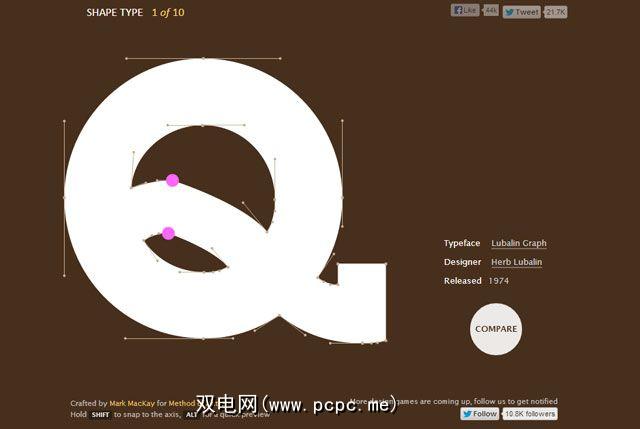
Shape Type是一款比上述游戏更难的游戏。您必须将字母的轮廓拖到屏幕上,然后创建形状适当,美观的字母。字母被故意弯曲变形,而您对字体的熟悉程度将决定您如何正确地正确调整它们的形状。您会再次接近原始图像。
核类型和形状类型由马克·麦凯(Mark Mackay)开发。两种HTML5游戏都具有多点触摸功能,并且可以在触摸屏上播放。
TypeConnection
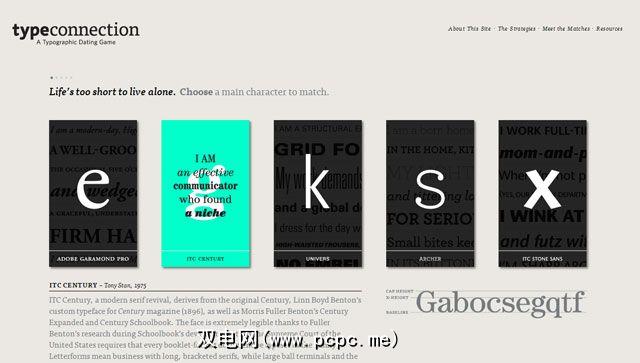
我们之前已经详细介绍了设计极为出色的“排印约会游戏"。字体还需要一种叫做和声的东西才能和谐共处。就像现实生活中的角色一样,寻找与伴侣之间良好关系的最佳选择。 TypeConnection允许您播放丘比特并使字体相互匹配。只有最好的夫妻才能做到。您可能正在扮演天使,但也有很多收获—学习印刷术术语,类型历史,以及正确的配对。如果您真的想真正输入文字并了解印刷术的更多信息,那么该网站的“资源"页面是一个宝库。
我喜欢印刷术
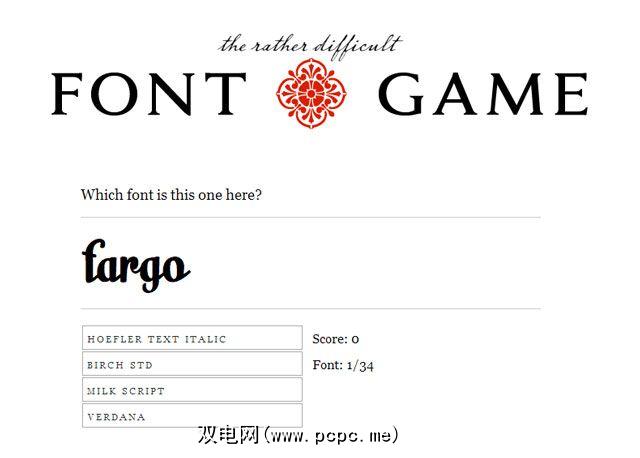
这是一个简单的字体标识游戏。系统会以四种可能的答案的形式为您提供字体和提示。正确对待它们,您的分数就会提高。您可能喜欢排版,但是如果您来自仅由Ariel,Times Roman和Comic Sans统治的地方,那么这是一个困难的游戏。您还可以使用移动版本并随身携带,以使移动时的字体知识更加轻松。
Ragtime
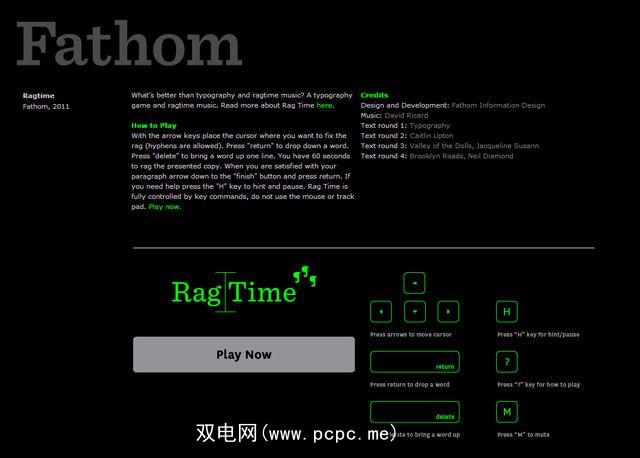
“标记不完整"是指沿页边距的印刷对齐方式。更具体地说,该行在段落的右侧断开。字体对齐对于所需的设计输出极为重要。 Ragtime是一款定时游戏(60秒),它会挑战您使用方向键来修复文本块。您必须始终使用箭头键正确对齐文本,同时还要在ragtime音乐在背景中嗡嗡作响时一直集中注意力。
拍摄衬线
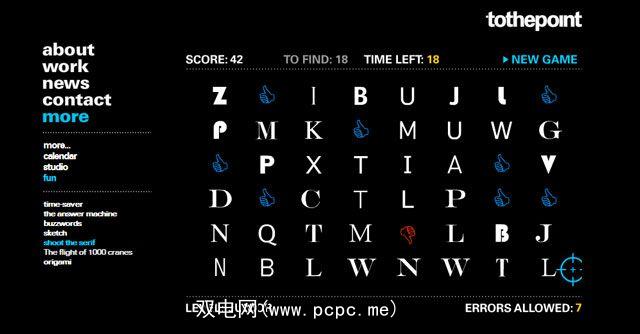
一个建议。请勿将耳机插入最大音量。枪声几乎把我的耳朵打断了。但这就是游戏,您可以在其中证明找到衬线并将其击落的速度。您必须在争分夺秒地射击。该游戏具有多个级别,而且难度逐渐增加……但是最终,您可以掌握枪支,并清楚了解衬线字体和无衬线字体之间的区别。
Helvetica
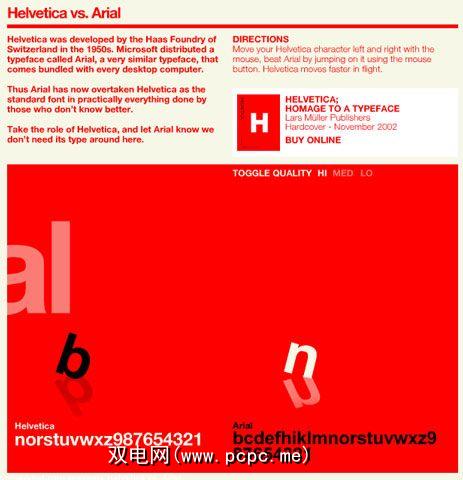
这是一个报仇和报应的故事。上面的屏幕截图告诉您有关两种字体– Ariel和Helvetica之间的不良情况。 Helvetica渴望血液,它以您的形式出现。这是我们大家都喜欢在两次会议之间在办公室玩的那些浪费时间的游戏之一。
海报信件[不再可用]
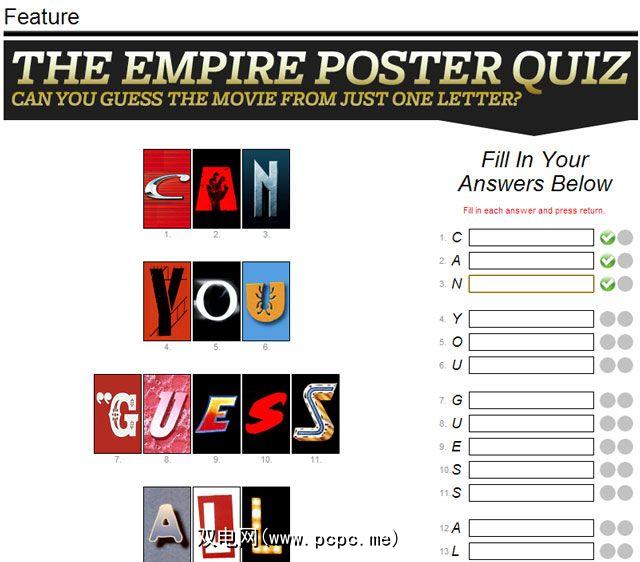
我们对印刷汗水知之甚少用于设计电影标题和海报的印刷元素。通常,它们是从头开始的,其中一些使其进入电影名人堂。例如:教父和星球大战。风格化的名称与成功电影中的角色一样可识别。海报字母是一个简单的测验,您可以通过查看单个字母的视觉提示来猜测电影的名称。当然,您可以通过单击字母的图像来作弊...但是要抵制这种冲动,直到您开始撕开头发。
键入War
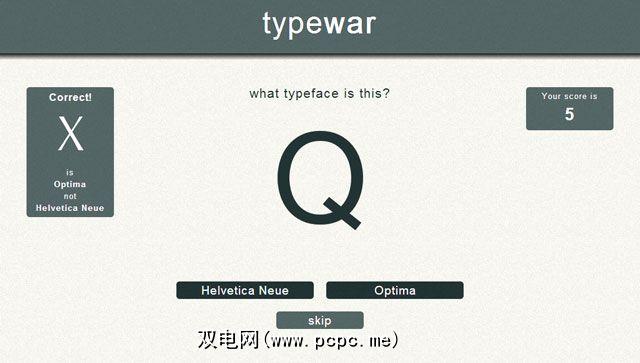
足够简单的字体识别测验应该有助于锻炼大脑的左右两侧。 Quests是Type War中的另一个测验,它会使用特定的字体和/或字母子集来测试您。以下是对“ Quest"的描述:
Arial vs. Helvetica Neue的大小写字母(注意:这包括实际上难以区分的字形。
您是哪种类型
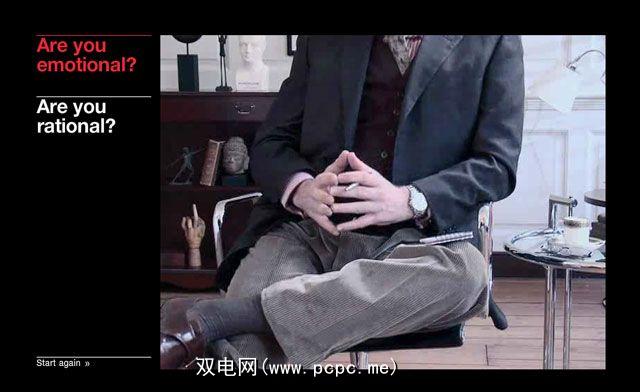
打开扬声器,因为这都是音频,这很有趣。与虚拟心理医生进行字体心理互动,虚拟心理医生通过询问一系列问题来试图找出哪种字体与您的个性相匹配。这是很切工的,很好地组合在一起。心理分析也不错,我发现我字体很漂亮,因为它们是由最好的艺术头脑精心组合而成的设计元素。这十个版式游戏表明它们也可以很有趣,但这的本质是字体是m不仅仅是一张漂亮的脸蛋。他们有历史,有个性。你同意吗?您对字体有多感兴趣?